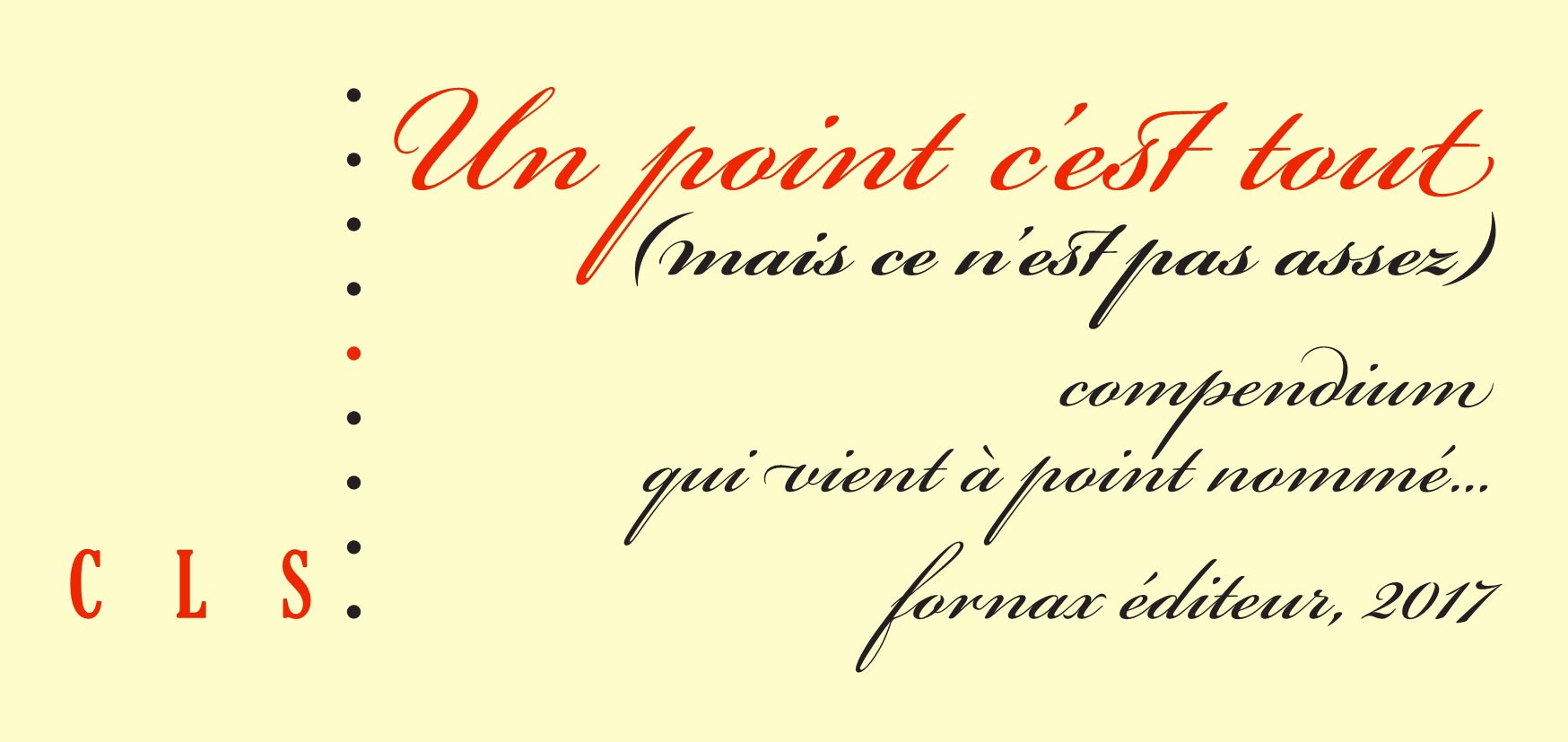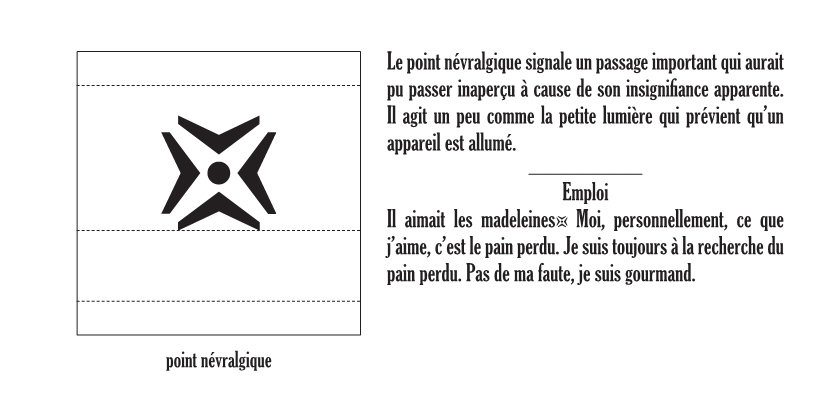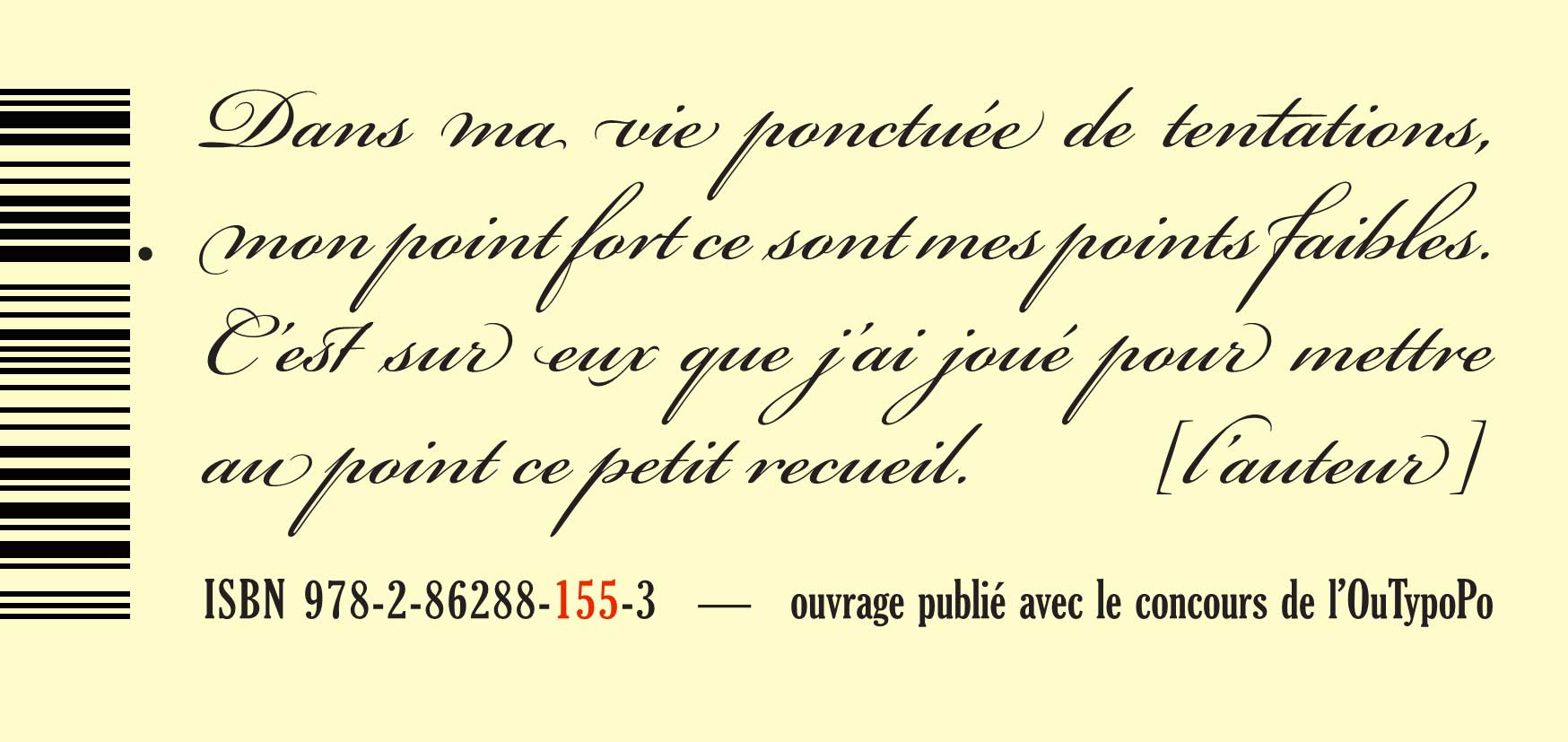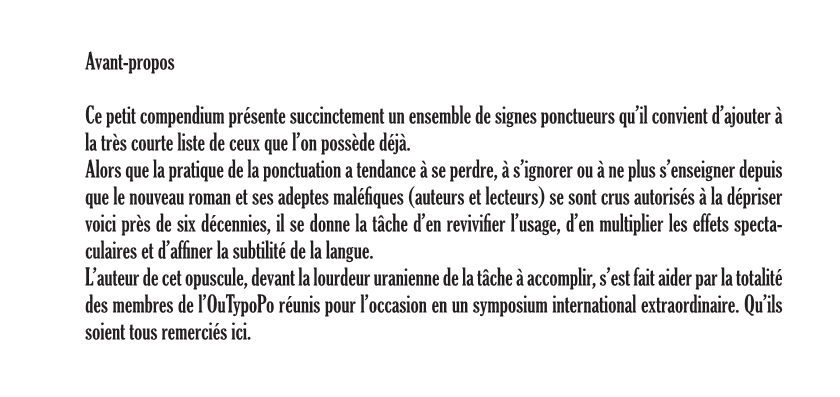
Bonjour à toutes, Encore ? Euh, oui. Pour annoncer la sortie (lundi prochain) d'un petit compendium Un point c'est tout, qui propose 32 signes de ponctuation nouveaux et un modèle de leur emploi. Quelques images pour illustrer la chose (1re et 4e de couv, avant propos, une page d'exemple) ; celles d'entre vous qui ont des ordinateurs qui rament voudront bien me pardonner leur présence. Autre sujet, pas trop éloigné. Retour sur la façon de présenter les citation dans les citations dans les citations, dans les... (on aura compris). On passera sur le fait que ce cas de figure est rare et que stupide est l'auteur qui s'y adonne si ce n'est par jeu. Une solution simple et élégante pour se sortir de ce guêpier serait d'imaginer des chevrons multiples (ouvrants et fermants) dont le nombre est inversement proportionnel au nombre de citations enchâssées. Un exemple pour mieux être compris (je simule les chevrons multiples à l'aide des guillemets doubles et simples) : ... texte texte texte «« début citation 1er niveau «‹ début de citation 2e niveau « début citation 3e niveau ‹ citation 4e niveau › fin citation 3e niveau » fin citation 2e niveau ›» fin citation 1er niveau »» texte texte texte. Ainsi, dès le début de la première citation, on sait quel est le nombre de citations enchassées : 5 chevrons = 5 citations ; 4 chevrons = 4 citations, etc. L'idée, vous l'aurez toutes compris, est fille de celle utilisée par Raymond Roussel dans les Nouvelles Impressions d'Afrique, mais inversée et avec des chevrons au lieu de parenthèses. Dans l'espoir de vous avoir été inutile, croyez bien toutes en mes souhaits de bonnes journées à venir, --